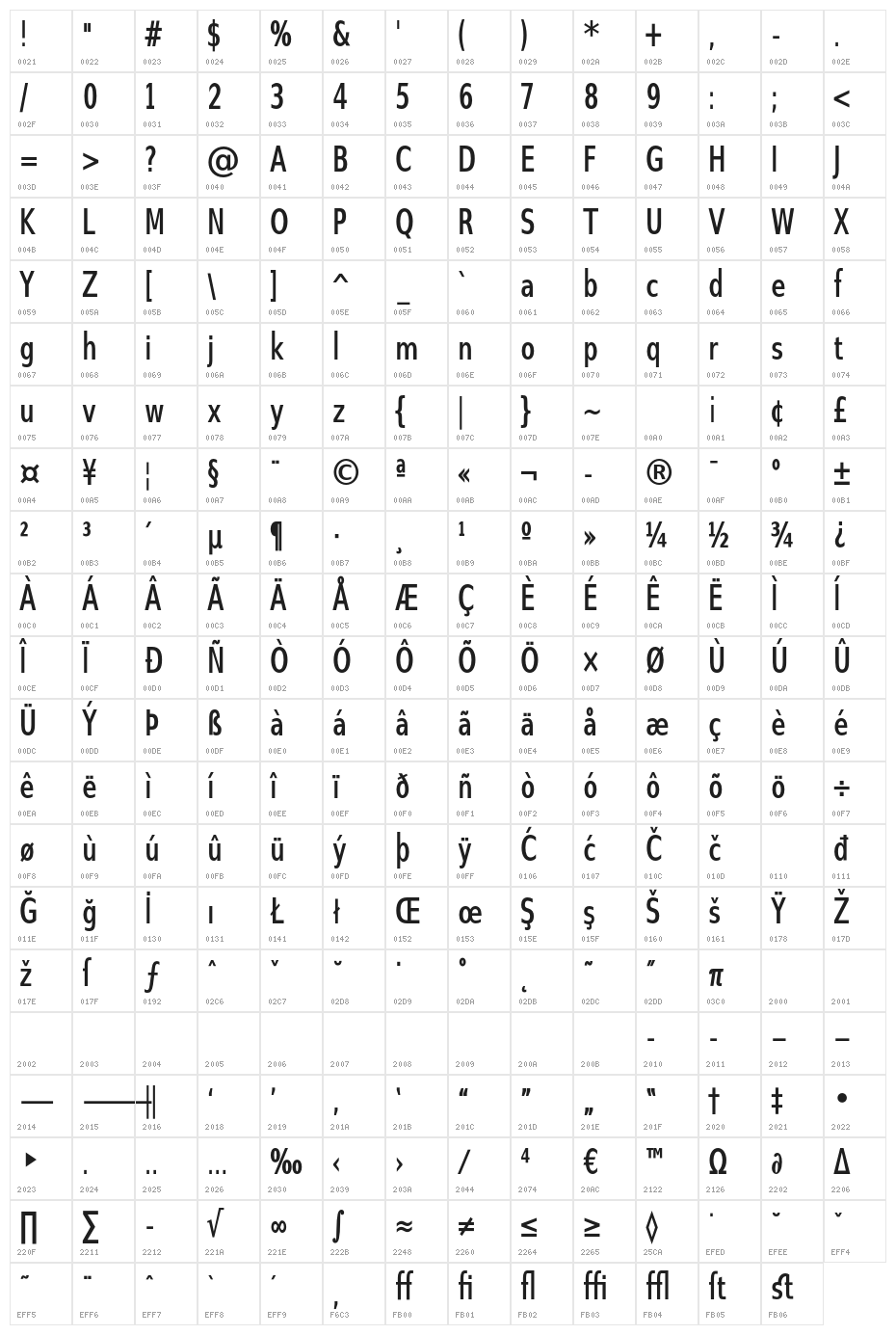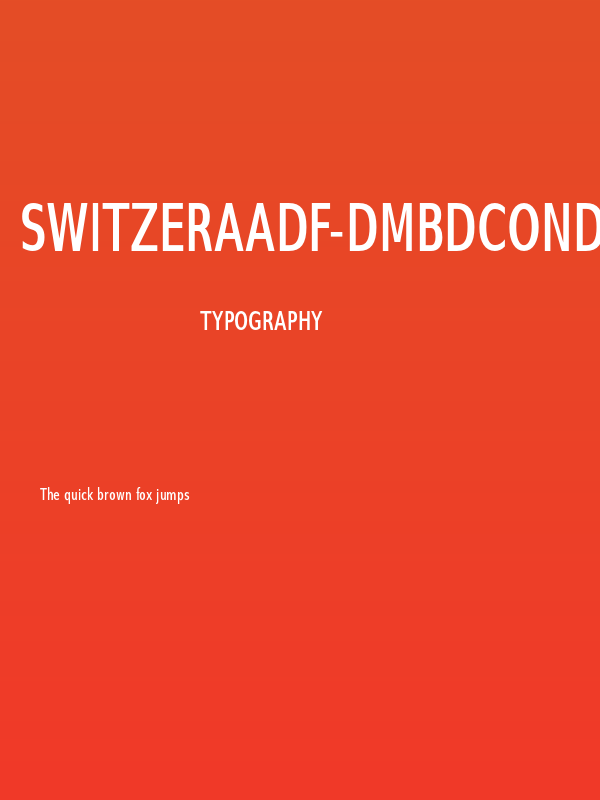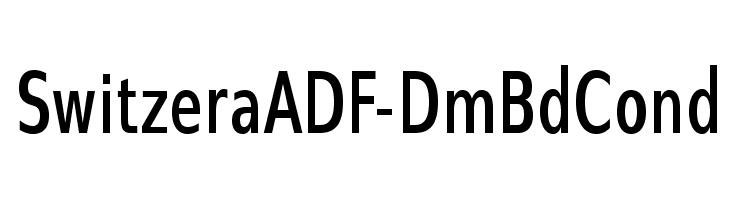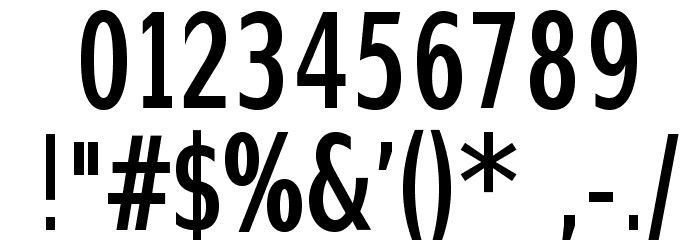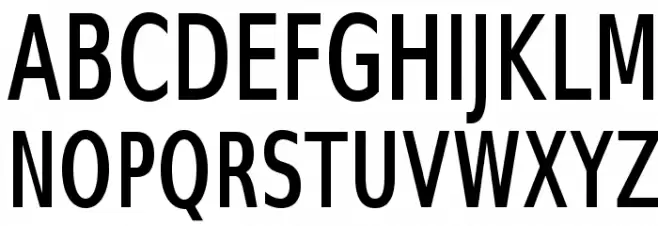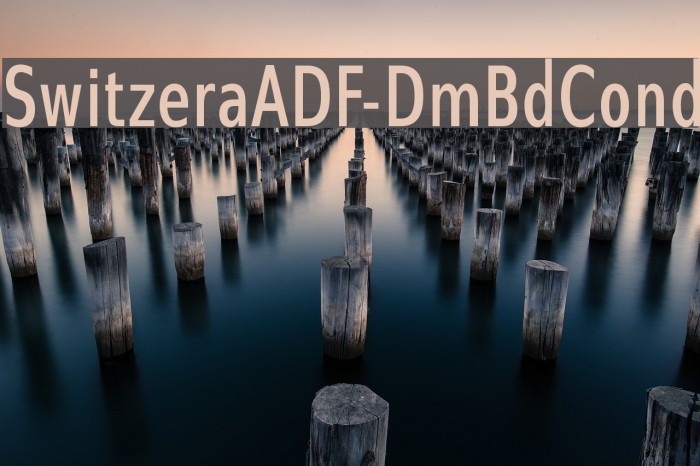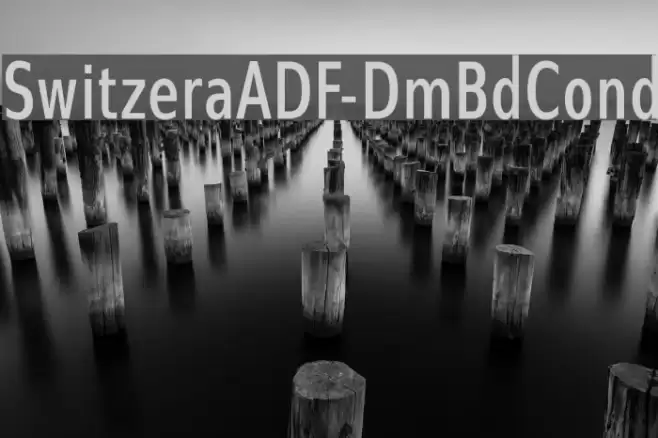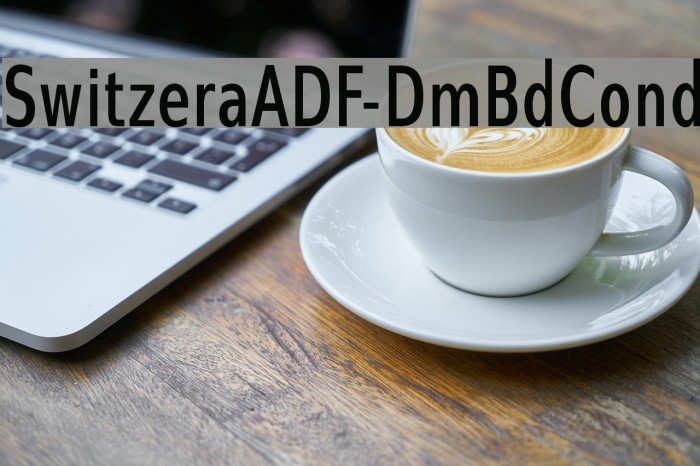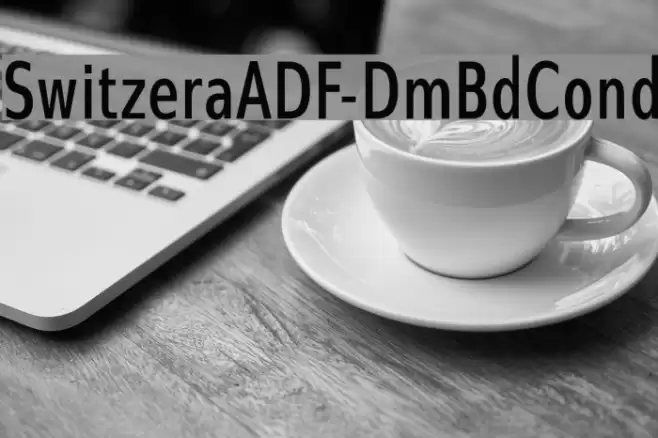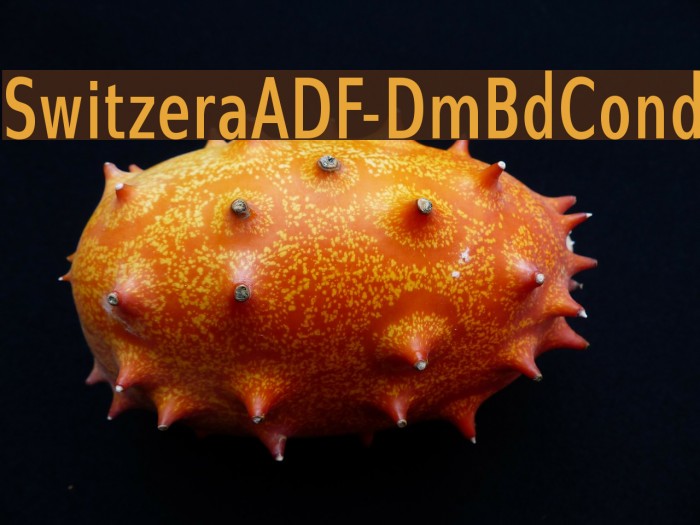
SwitzeraADF-DmBdCond Font
| Anwendungsfall | Headlines, Logos, Branding |
| Vorgeschlagene Projekte | Ideal for branding, advertising, headlines, and editorial design where a strong and clear typeface is needed. |